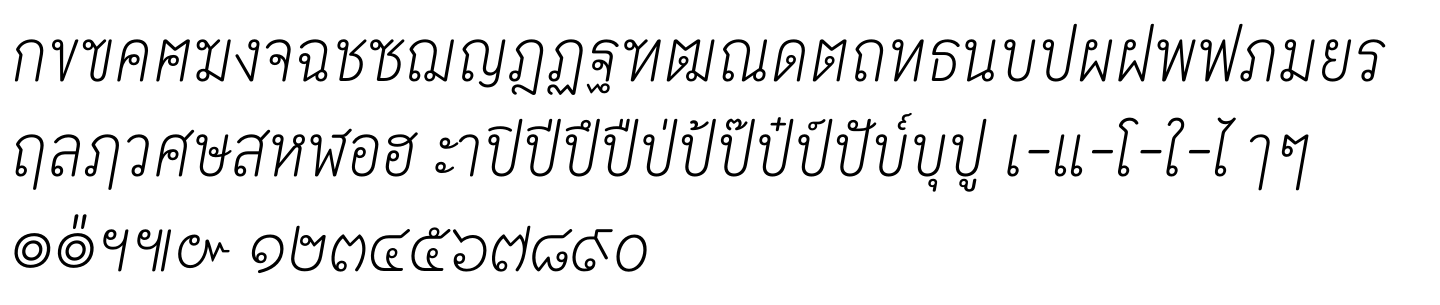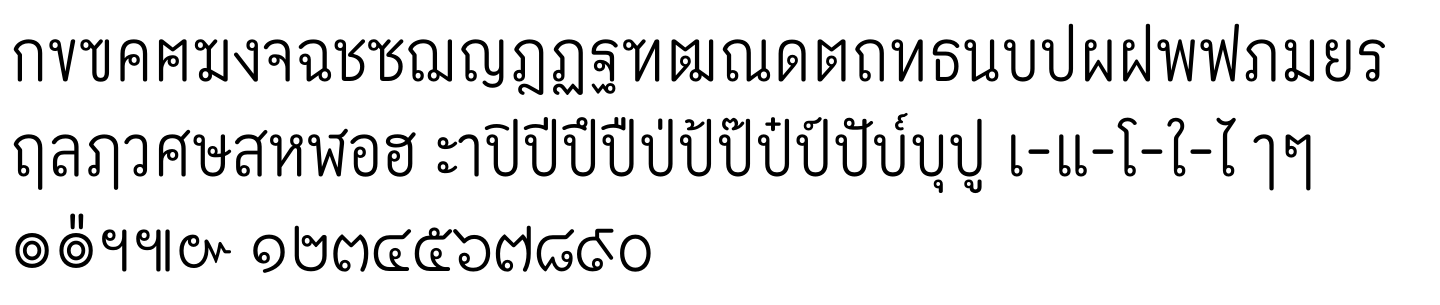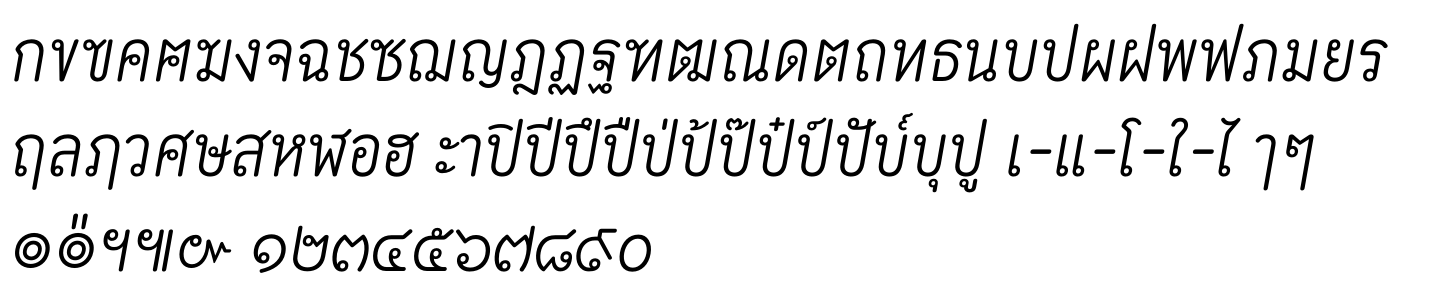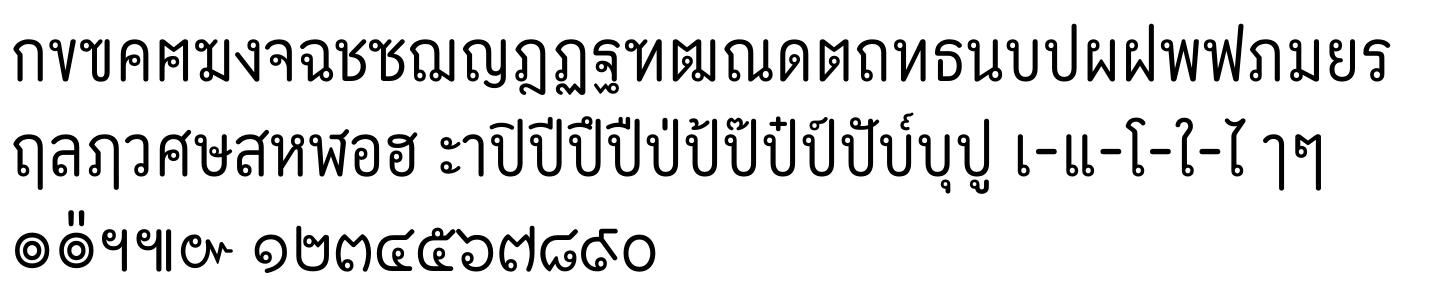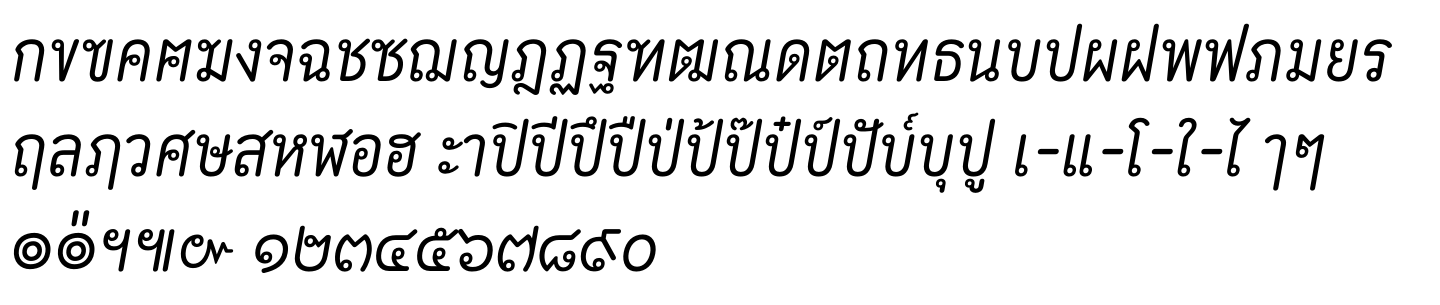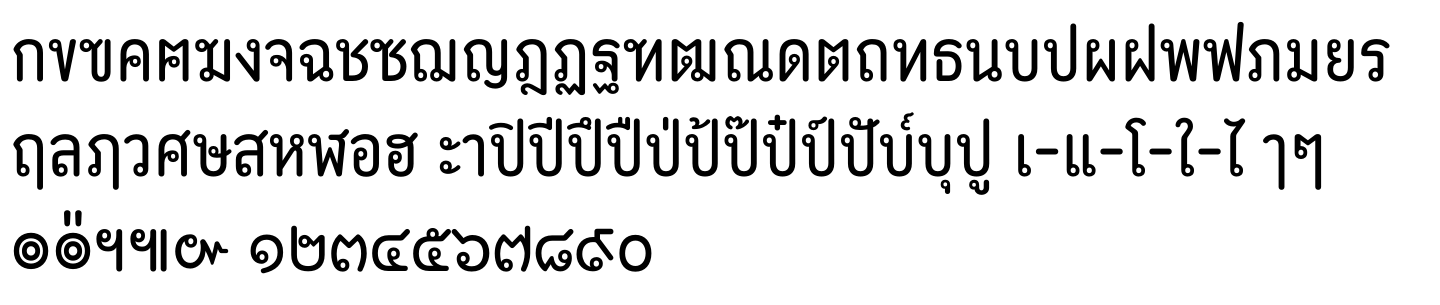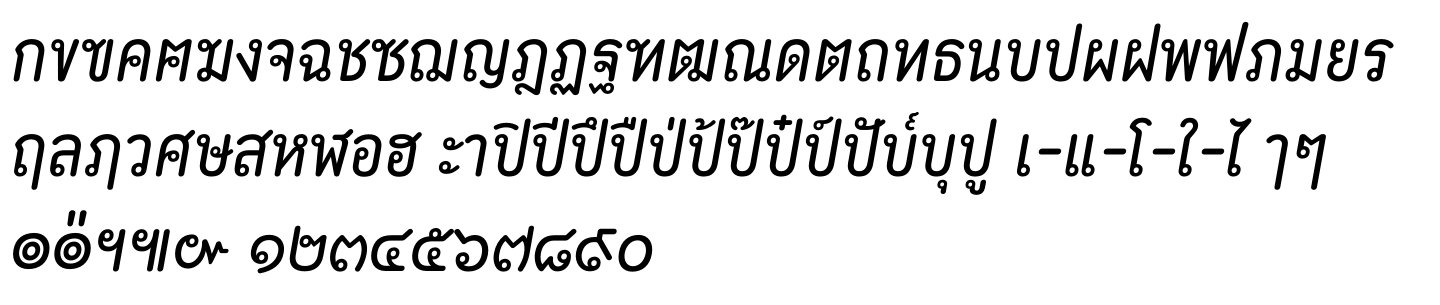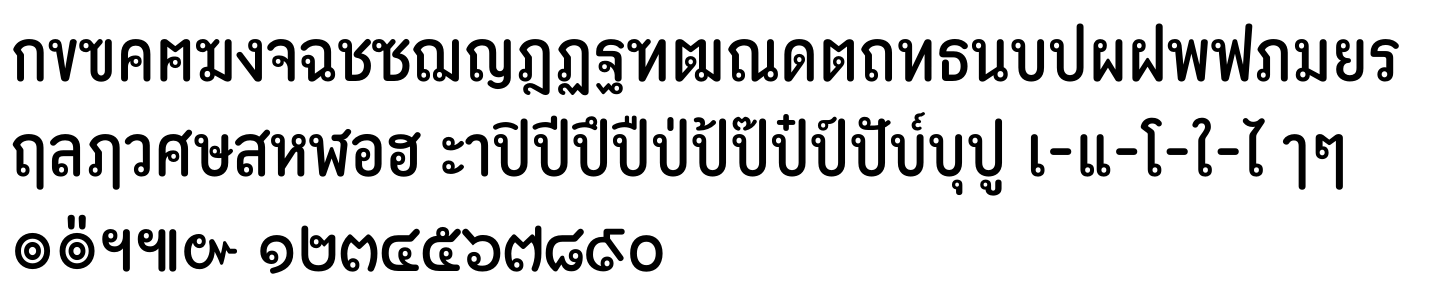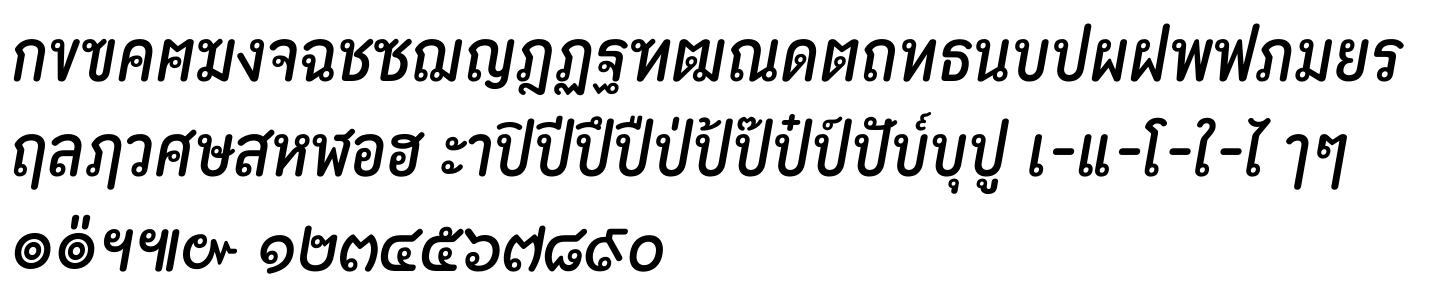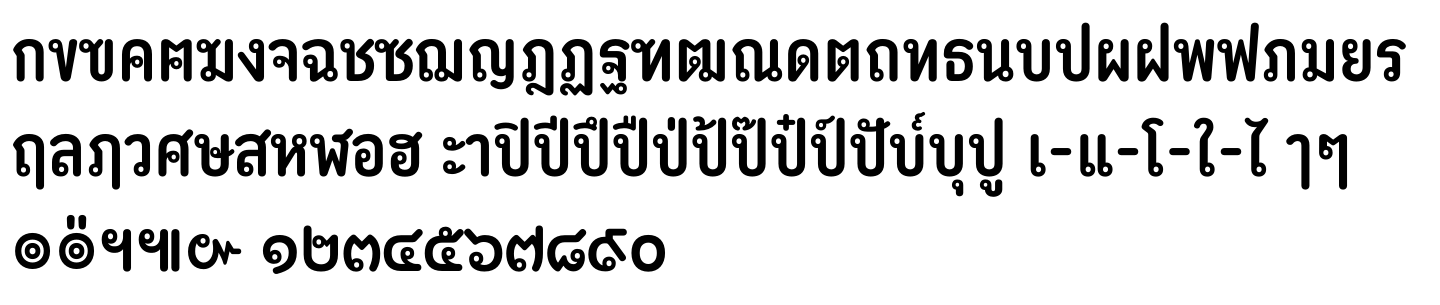
DB ChatGen Rounded Narrow
ดีบี ชัดเจน ราวนด์ แนโรว์
DB ChatGen Rounded Narrow เฉพาะ ปลายมน ตัวแคบ
หนึ่งในสมาชิกครอบครัว DB ChatGen ที่มีทั้ง ปลายตัด ปลายมน ตัวปกติ ตัวแคบ ตัวกว้าง และตัวเอน
DB ChatGen
เมื่อคุณต้องการ chat กับคนทุก gen ให้ชัดๆ
- ดีบี ชัดเจน เป็นฟอนต์ลูกครึ่ง ไทย-ฝรั่ง.
- หัวกลมแบบไทยเอาใจ สว. หุ่นเท่แบบฝรั่งเอาใจวัยทีน.
- ไม่ได้ยืมโครงสร้างงอักษรฝรั่งมาใช้แค่ให้ดูทันสมัย แต่ตั้งใจนำมาใช้แก้ปัญหาคู่สับสนในฟอนต์ตัวพื้นแบบจารีต เช่น ข-ช, ด-ต ฯลฯ
- ข ไข่ ใช้ทรง V เพื่อให้ดูแตกต่างชัดเจนจาก ช ช้าง ทรง R กลับหัว
- ต เต่า ใช้รอยหยักเต็มความกว้างแบบ M เพื่อให้แยกแยะง่ายจาก ด เด็ก.
- จิ๋วก็แจ๋ว ใหญ่ก็แจ่ม. ใช้ขนาดตัวจิ๋วบนฉลากบรรจุภัณฑ์ก็ไม่ต้องเพ่ง, ใช้ขนาดตัวใหญ่บน signage อาคารก็อ่านง่ายจากระยะไกล.
- ครอบครัวตัวพิมพ์ใหญ่มโหฬาร มีให้เลือกใช้อย่างจุใจถึง 90 สไตล์ !!!
- ตัวสัดส่วนมาตรฐาน (Std) ใช้เป็นได้ทั้งตัวพื้นแบบไม่เป็นทางการ และตัวพาดหัวที่เน้นอ่านง่ายในฟอนต์เดียว.
- ตัวกว้าง (Wide) ให้ความโปร่งสบายที่น้ำหนักบาง และความมั่นคงที่น้ำหนักหนา.
- ตัวแคบ (Narrow) เหมาะกับงานพาดหัวสื่อพื้นที่แคบอย่างมือถือ.
- ทั้งตัวมาตรฐาน, ตัวกว้าง และตัวแคบ ยังมีแบบปลายมน (Rounded) ที่ดูผ่อนคลายเป็นกันเอง ให้เลือกใช้.
- สร้างสื่อร่วมสมัยกับคนทุกเจนได้ ด้วย ดีบี ชัดเจน!
หมายเหตุ: ฟอนต์ที่คุณเพิ่งอ่านผ่านตาไปคือ DB ChatGen.